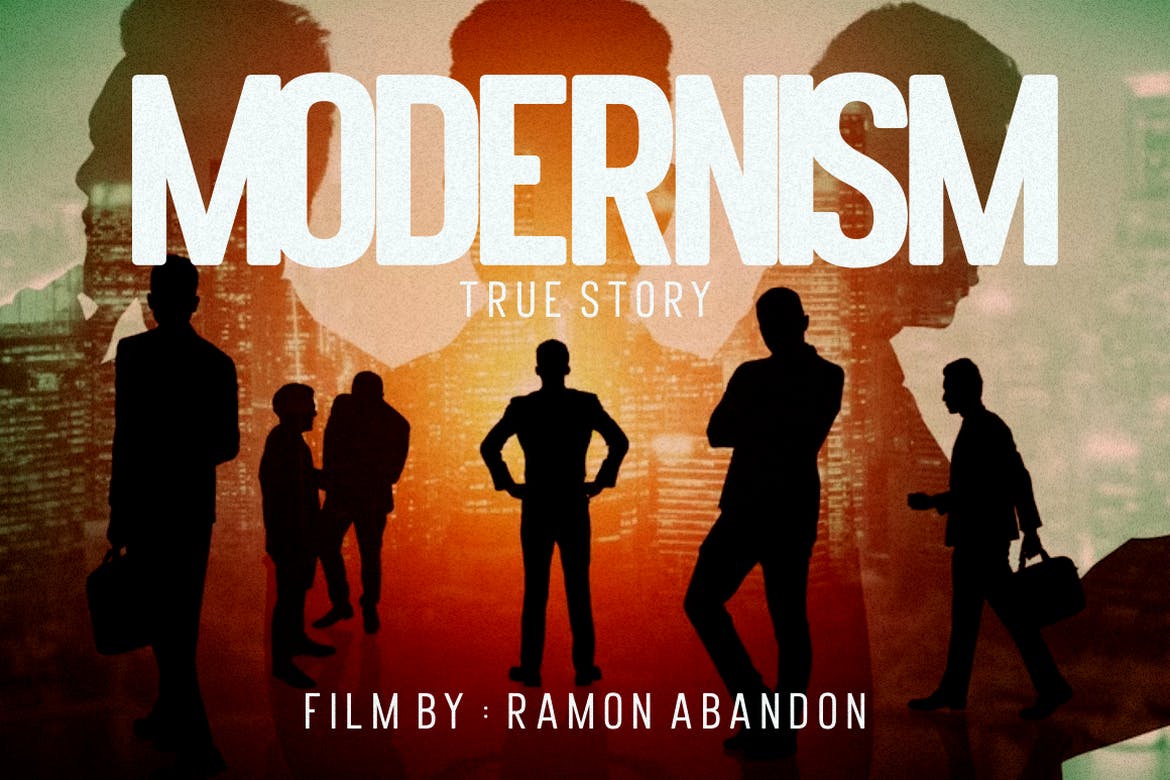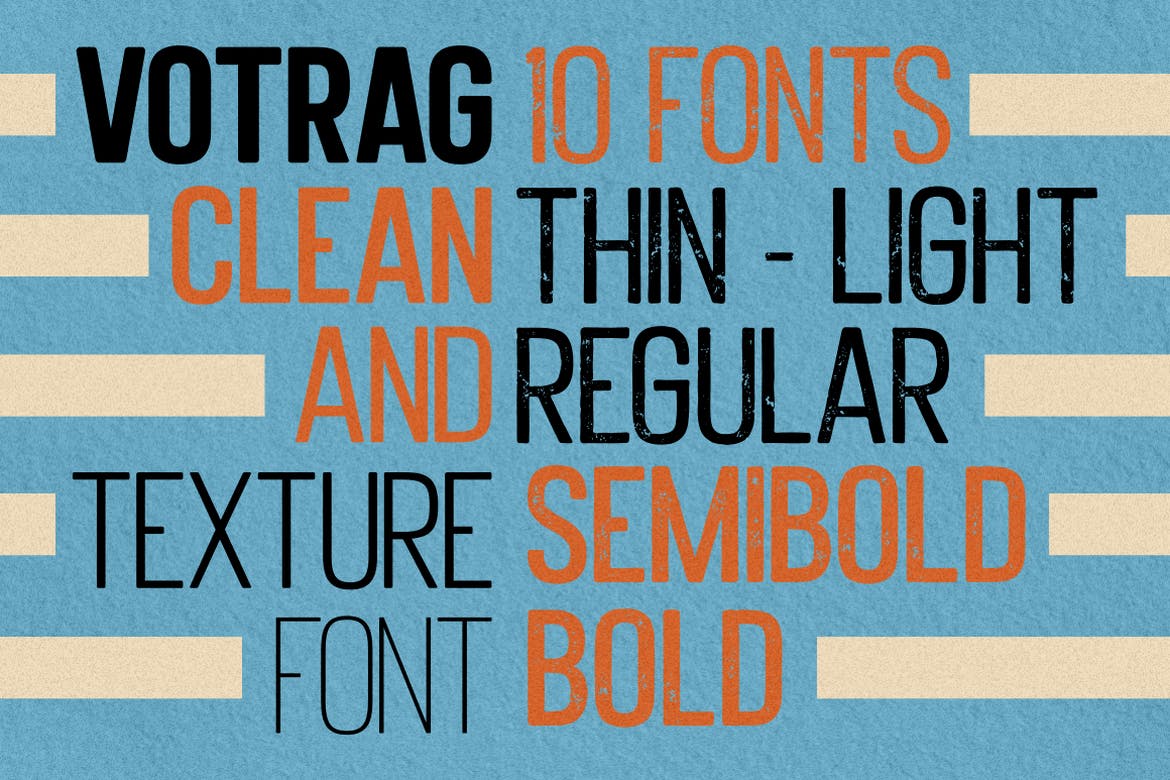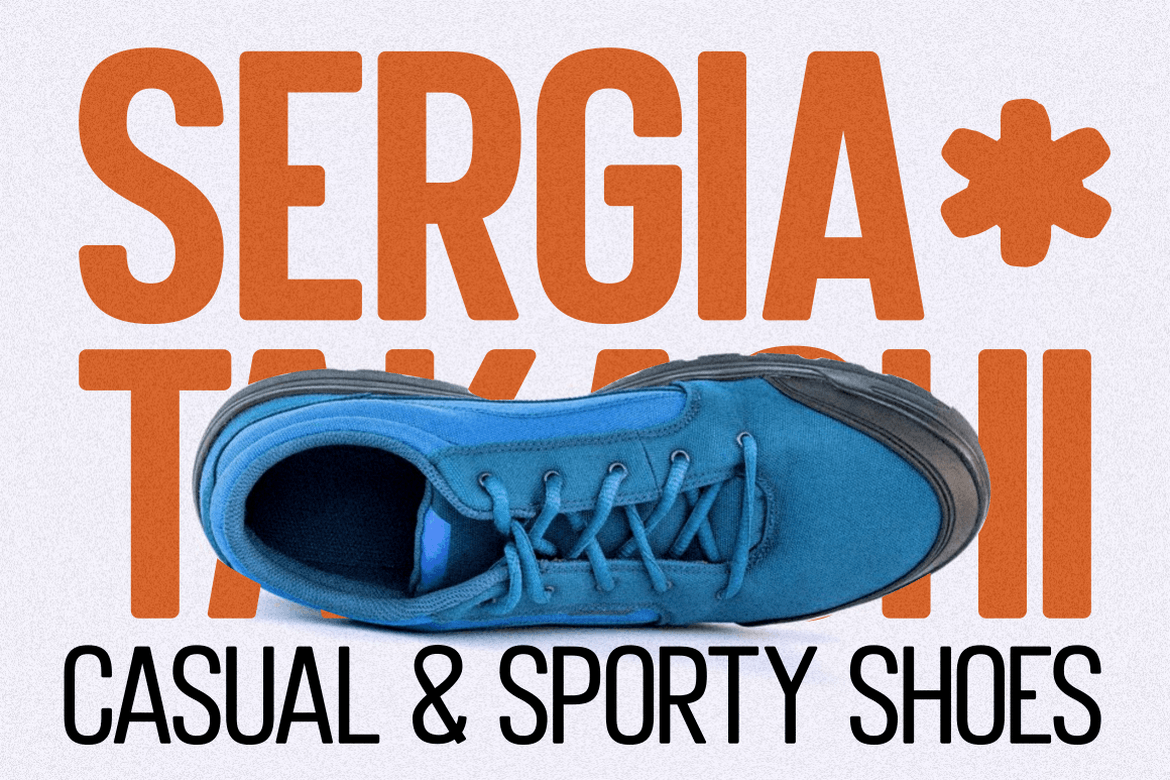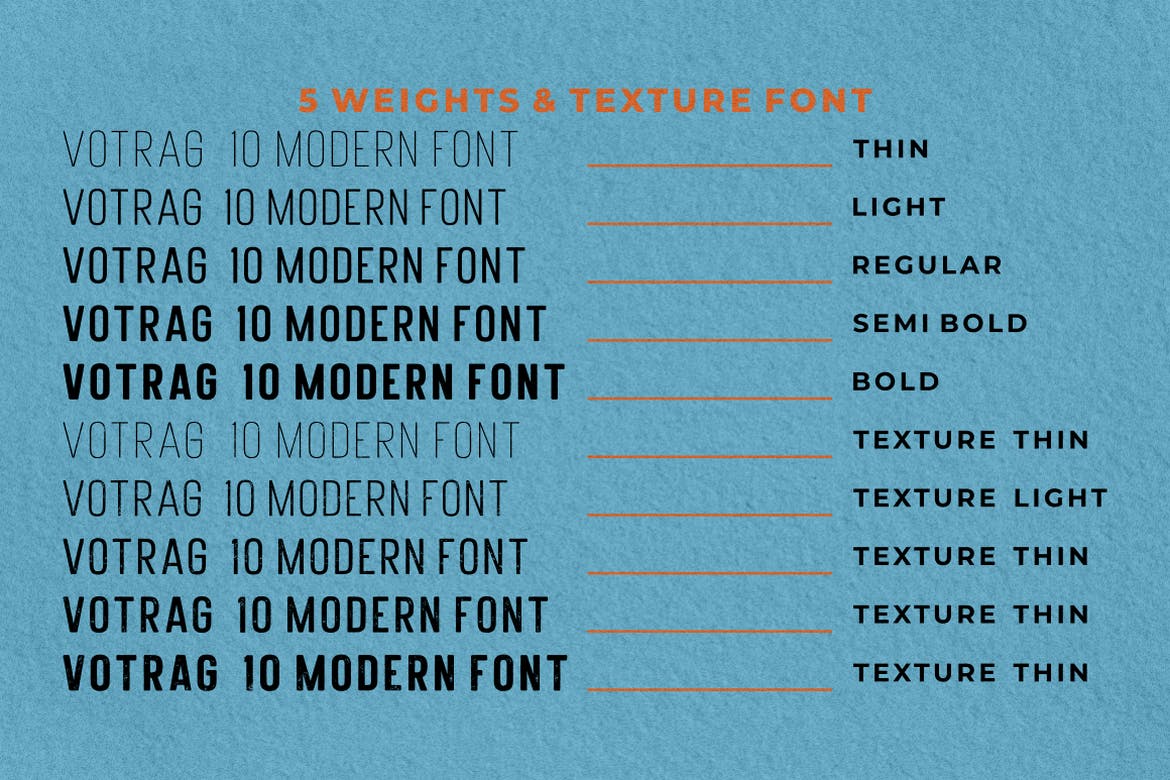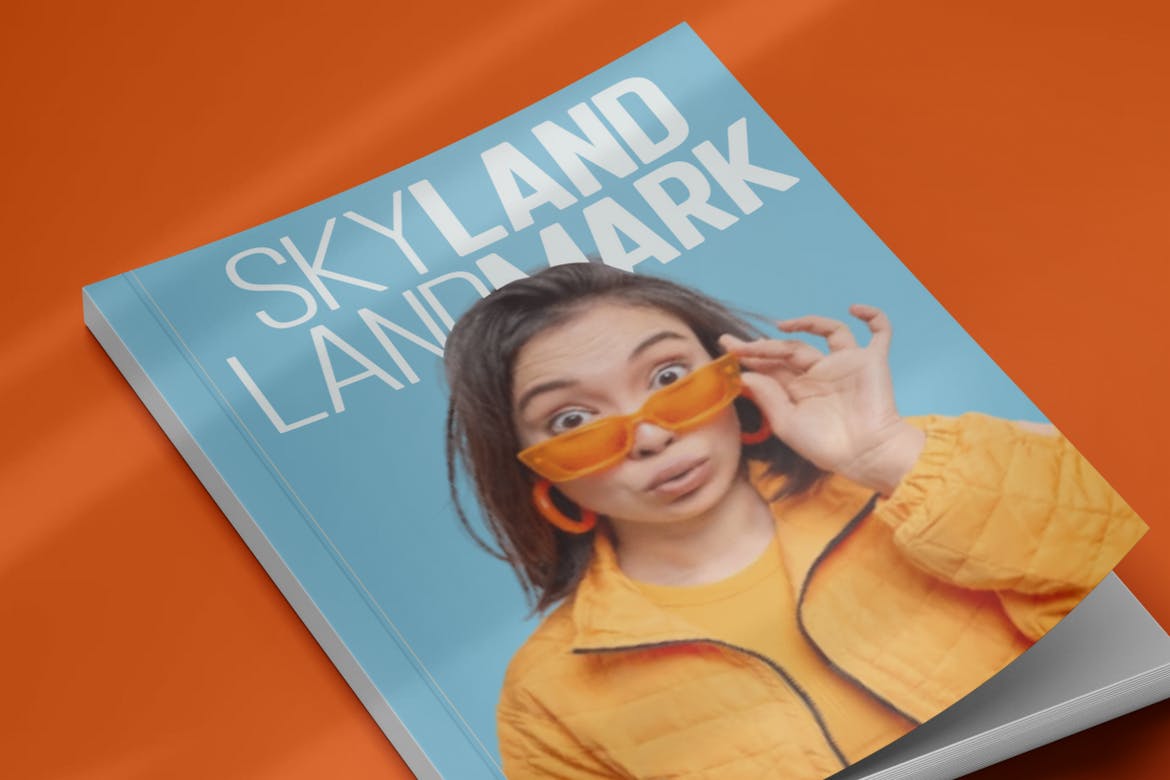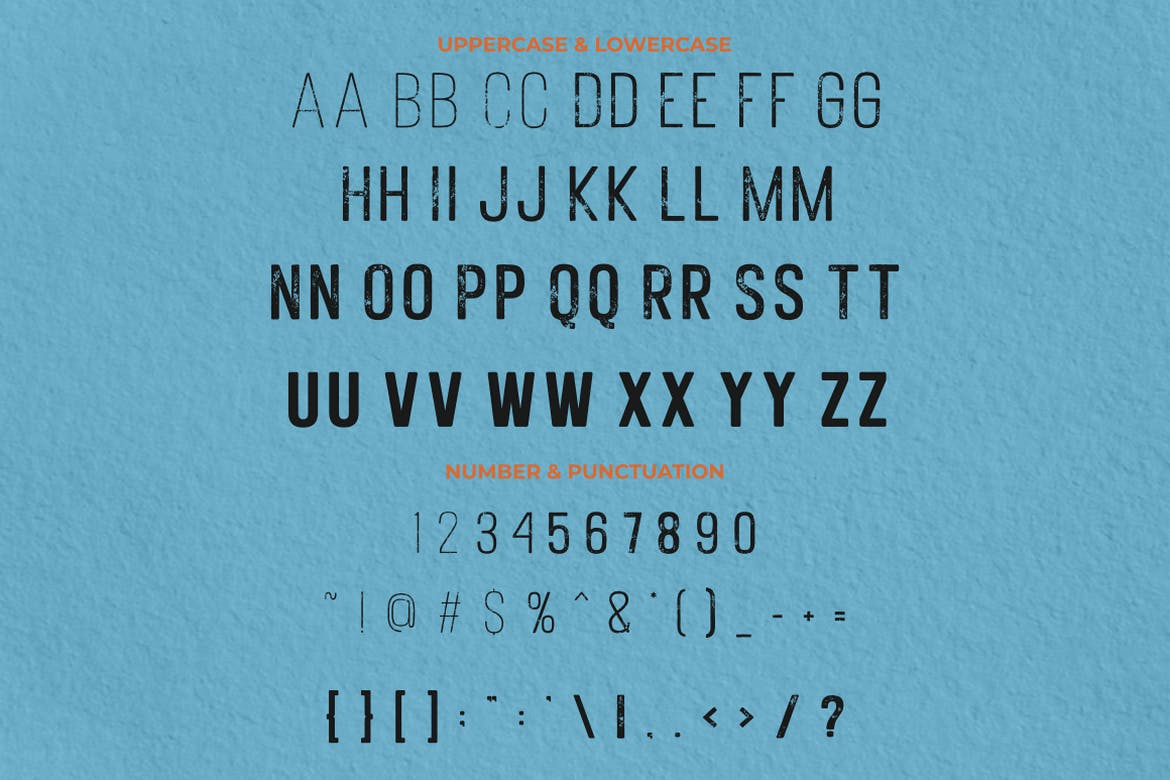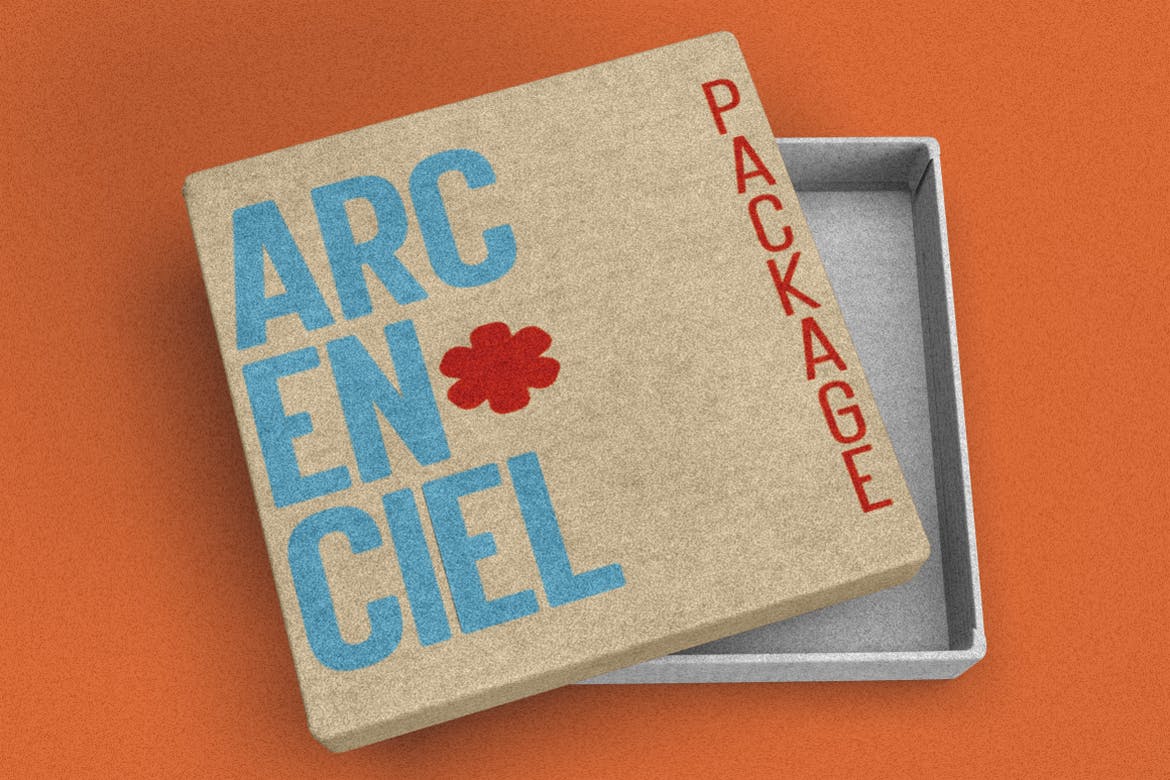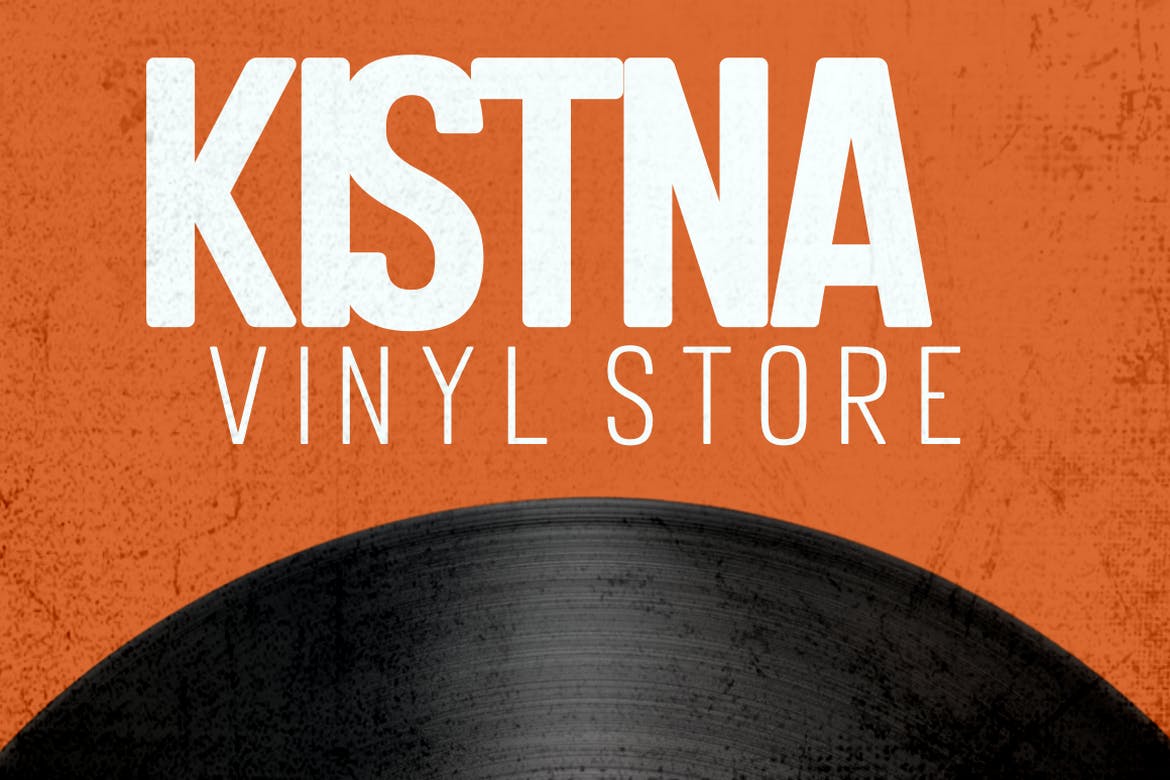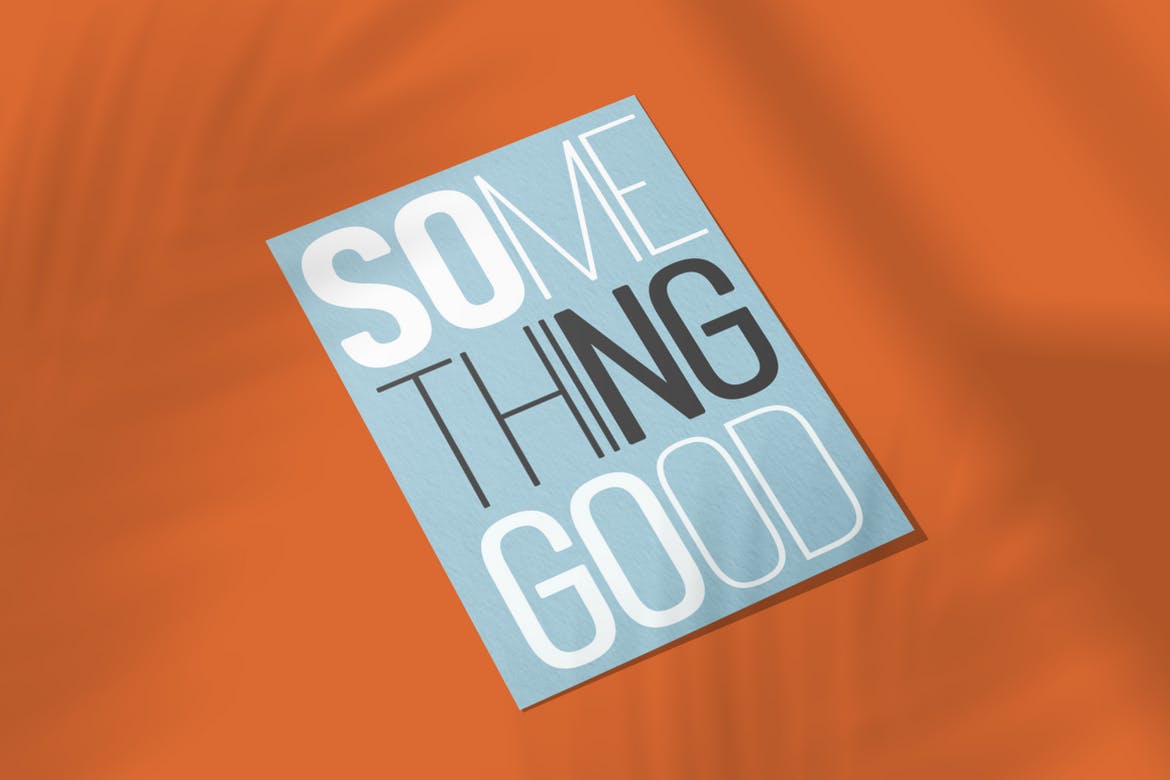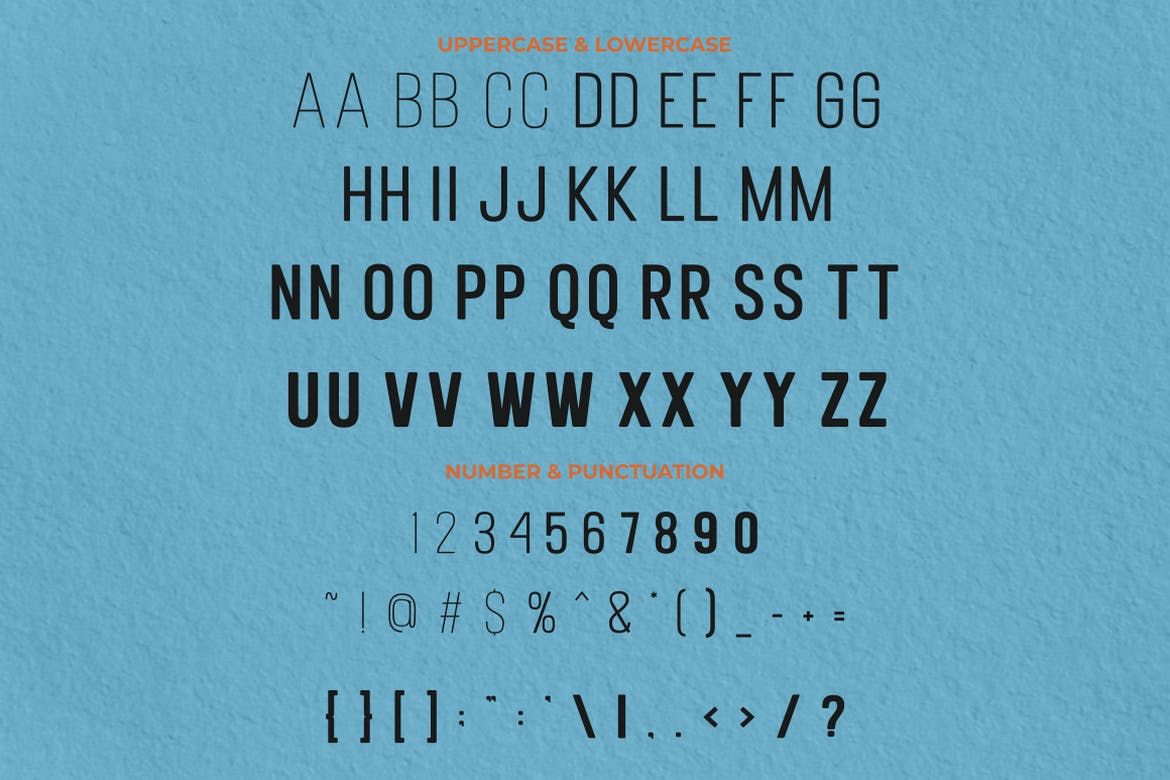
Votrag - فونت مدرن
معرفی Votrag - مجموعه 10 فونت مدرن، یک مجموعه تایپفیس چندمنظوره که شامل طیف وسیعی از امکانات طراحی است. با پنج وزن مختلف - نازک، سبک، معمولی، نیمهکلفت و کلفت - هر یک همراه با نسخههای تمیز و بافتدار، Votrag مجموعاً ده فونت منحصر به فرد را ارائه میدهد. سبک بدون سر (sans-serif) با گوشههای گرد، حسی مدرن و شیک را به پروژههای شما اضافه میکند. خواه در زمینه برندینگ، طراحی لوگو، طراحی بستهبندی، مواد چاپی، فرمتدهی فایلها، استایلسازی عناوین، طراحی مجلات، سرخطها، پوسترها، برچسبها و فراتر از آن مشغول باشید، Votrag سفر خلاقانه شما را قدرت میبخشد.
مجموعه فونت مدرن Votrag دروازهای به دنیای بیپایان خلاقیت است. این مجموعه با ارائه دامنهای جامع از پنج وزن - نازک، سبک، معمولی، نیمهکلفت و کلفت - به همراه نسخههای تمیز و بافتدار، مجموعاً ده فونت چشمگیر را در بر میگیرد. سبک بدون سر، که با گوشههای گرد مشخص میشود، حسی از مدرنیته و شیک بودن را منتقل میکند. این چندمنظوره بودن، آن را به انتخابی عالی برای مجموعهای از کاربردها تبدیل میکند، از ارتقاء هویت برند شما و ایجاد لوگوهای جذاب تا بهبود زیباییشناسی بستهبندی، سازماندهی مواد چاپی، فرمتدهی فایلهای دیجیتال و بیان بیپروا با عناوین، طراحی مجلات، سرخطها، پوسترها، برچسبها و بیشتر.